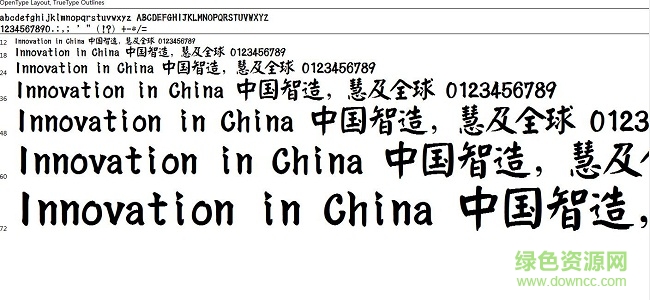
經(jīng)典簡(jiǎn)顏體字體
經(jīng)典簡(jiǎn)顏體字體是一款神形兼?zhèn)涞?a href="http://kiwanis-srv.org/k/shufaziti/" target="_blank">書法字體,該字體筆畫遒勁,穩(wěn)健厚重,氣勢(shì)恢宏,藝術(shù)性極強(qiáng),適用范圍廣泛,本站還有各種好看的字體,需要的朋友快來下載吧!
顏體書法特征
【從美學(xué)上論】
顏體端莊美、陽剛美、人工美,數(shù)美并舉,幽為后世立則。
經(jīng)典簡(jiǎn)顏體
【從特點(diǎn)上論】
顏體形顧之簇新、法度之嚴(yán)峻、氣勢(shì)之磅礴前無古人。
【從時(shí)代論】
唐初承晉宋馀緒,未能自立,顏體一出,唐斗壇所鑄新體成為盛唐氣象鮮明柄志之一。